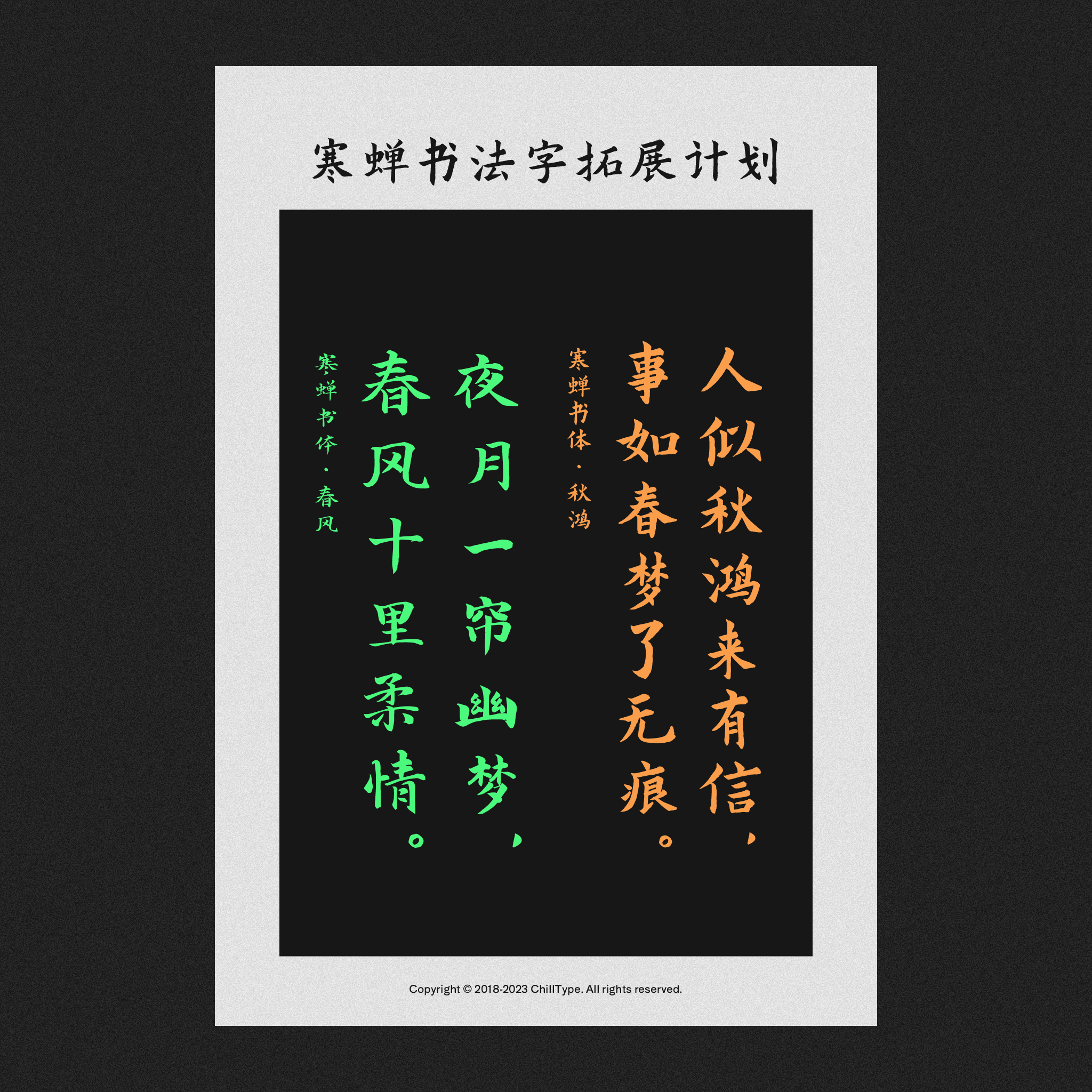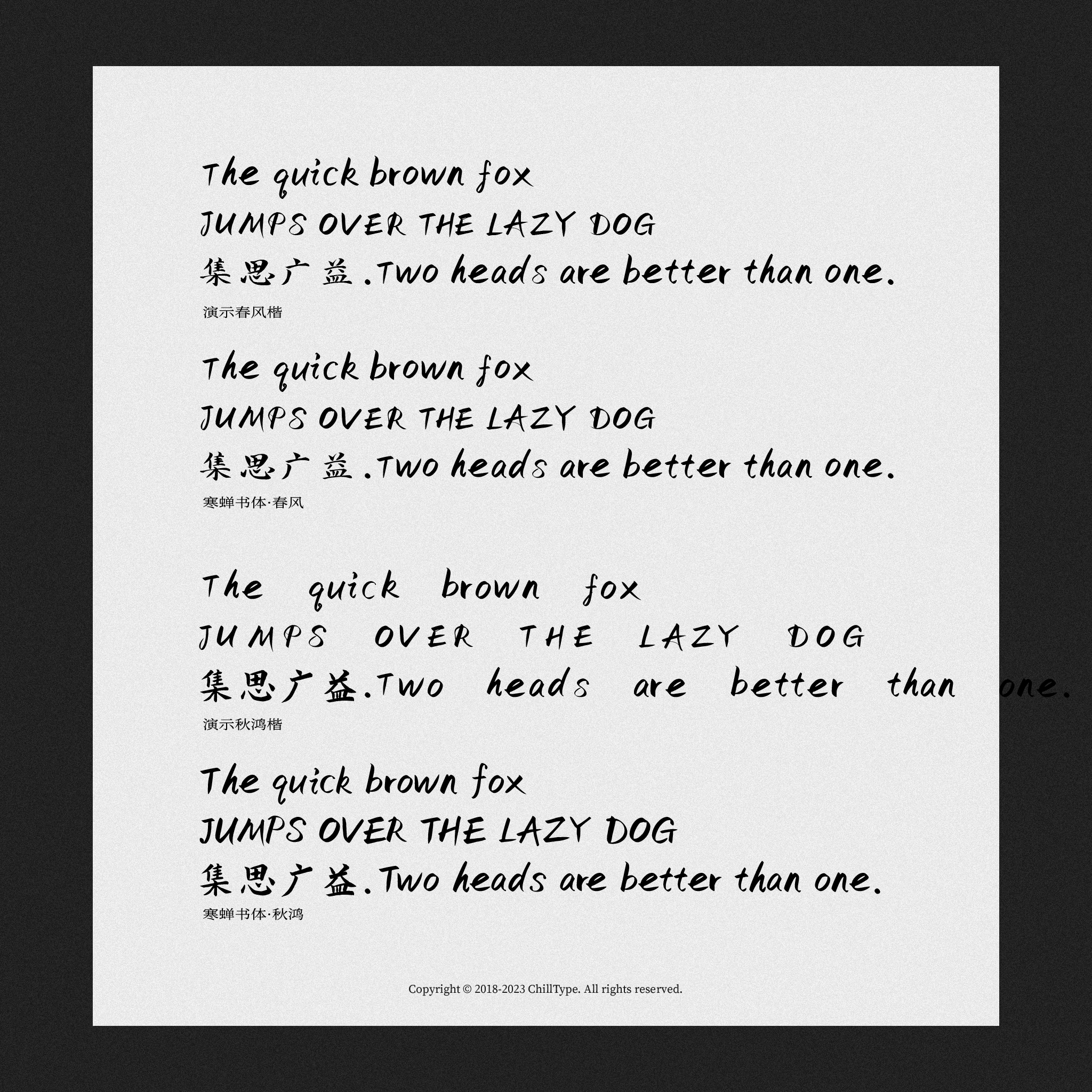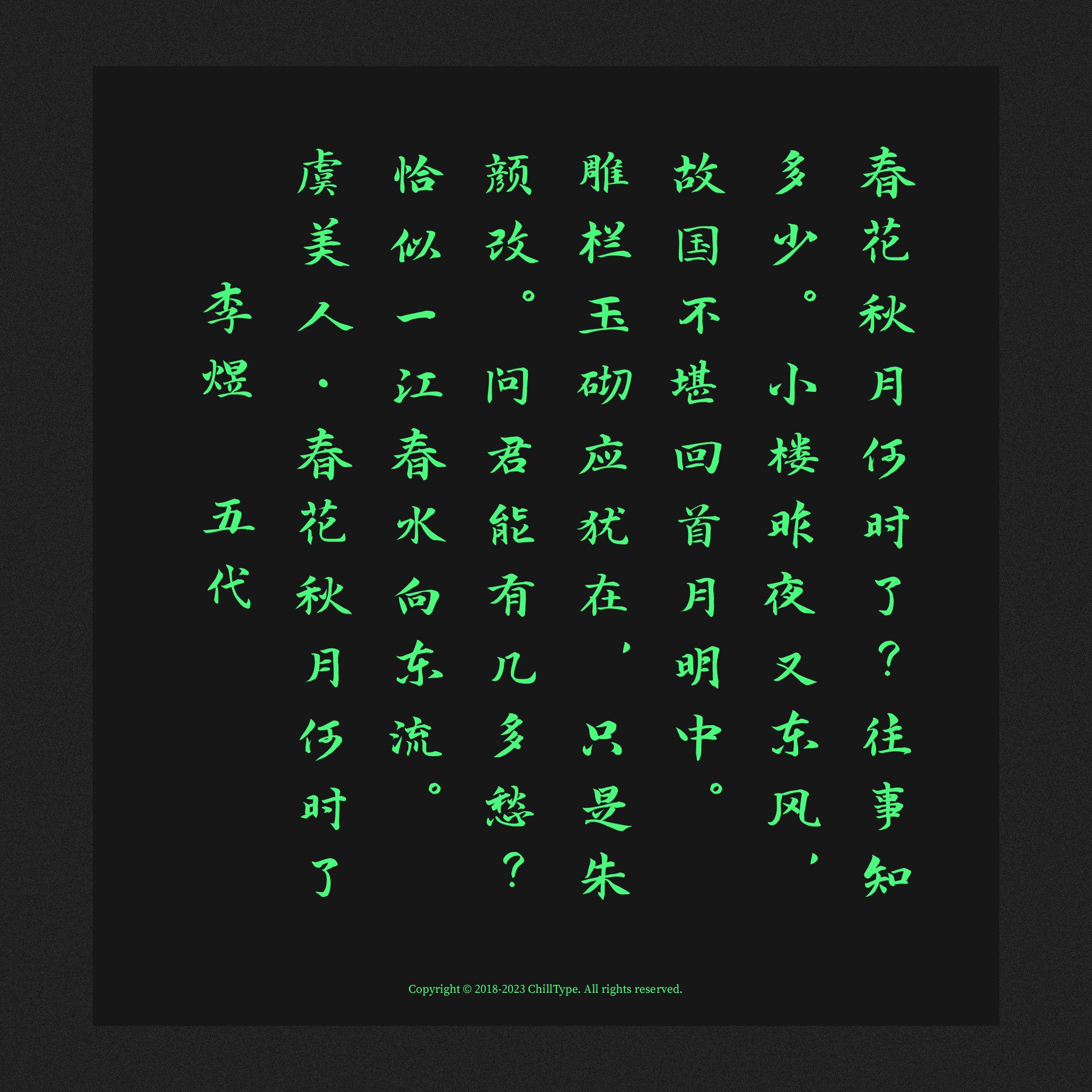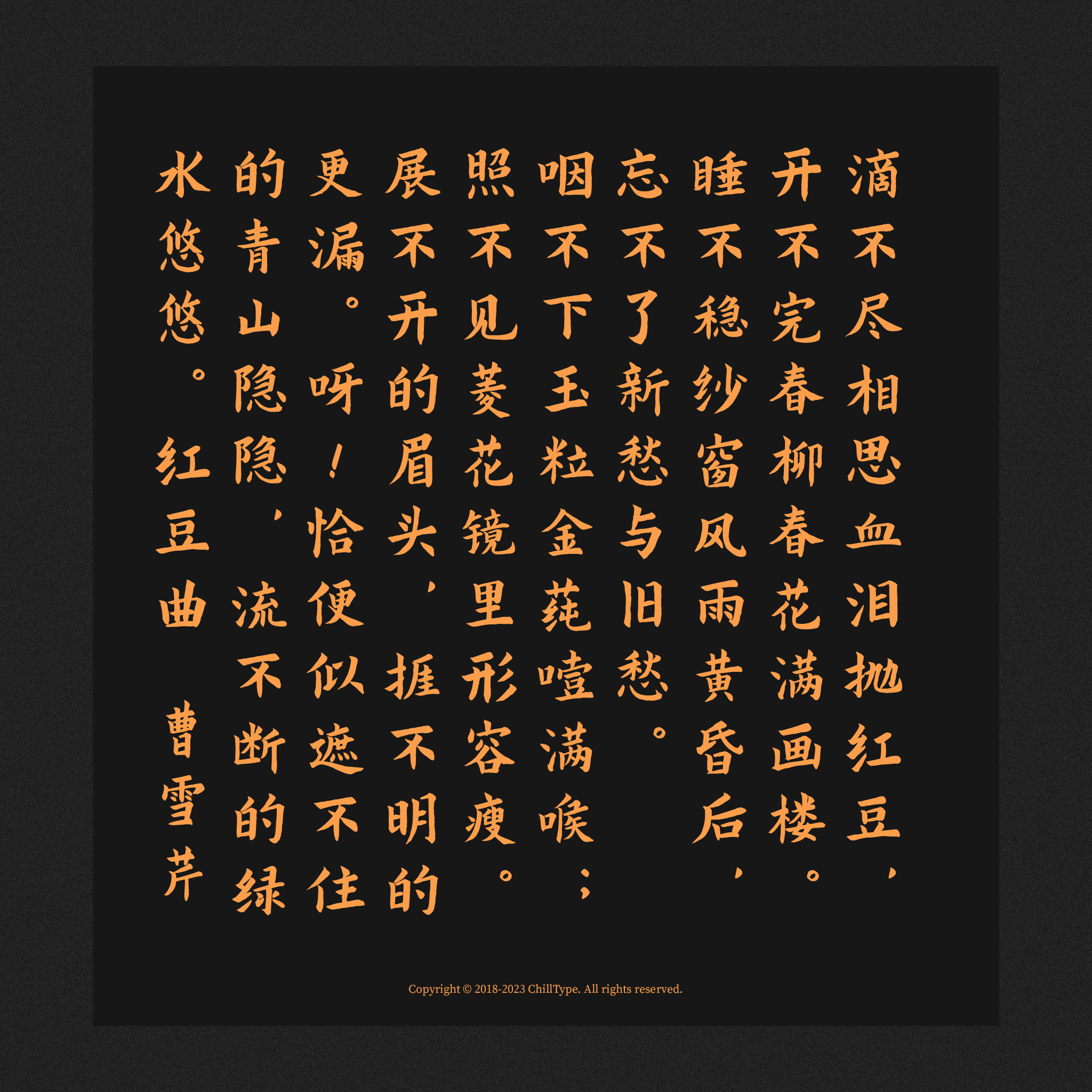
寒蝉书体春秋 是一项基于开源字体「演示春风楷」与「演示秋鸿楷」所进行的拓展字形项目,旨在继承并发展原有字体的设计风貌,通过扩充字形库以覆盖更广泛的使用场景,满足从日常排版到创意设计的多层次需求。原字体项目由 keynoteart 创作并维护,保留所有权利,其源代码及设计资料可通过 GitHub 仓库访问(https://github.com/maoken-fonts/slidefont)。本次拓展在保持原字体结构与美学特征的基础上,细致调整了部分笔画细节,并补全了多处字形空白,使整体视觉风格在统一中更显丰富与完整。
寒蝉书法字拓展计划海报,展示“寒蝉书体·秋鸿”(橙色)书写“人似秋鸿来有信,事如春梦了无痕”以及“寒蝉书体·春风”(绿色)书写“春风十里柔情,夜月一帘幽梦”。
妙造自然
展示四种不同字体样式的文本示例,每种包括英文句子“The quick brown fox JUMPS OVER THE LAZY DOG”和中文句子“集思广益. Two heads are better than one.”,并标注字体名称。
秋鸿字体书法样本,内容为曹雪芹的《临江仙·柳絮》。
李煜《虞美人·春花秋月何时了》书法作品
红豆曲 曹雪芹 书法作品,以竖排橙色字体呈现全曲内容